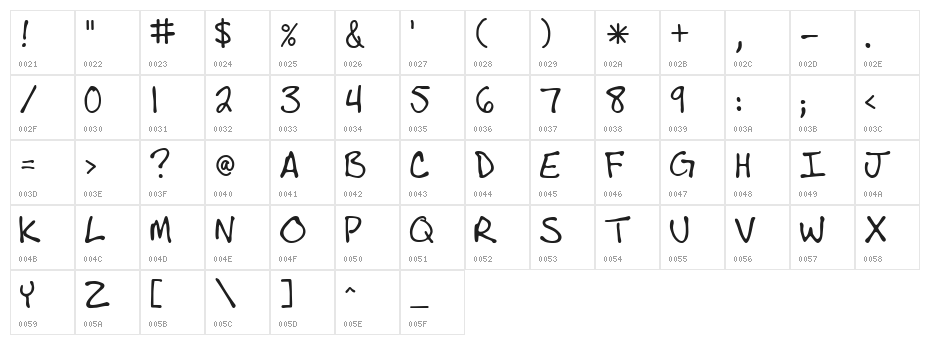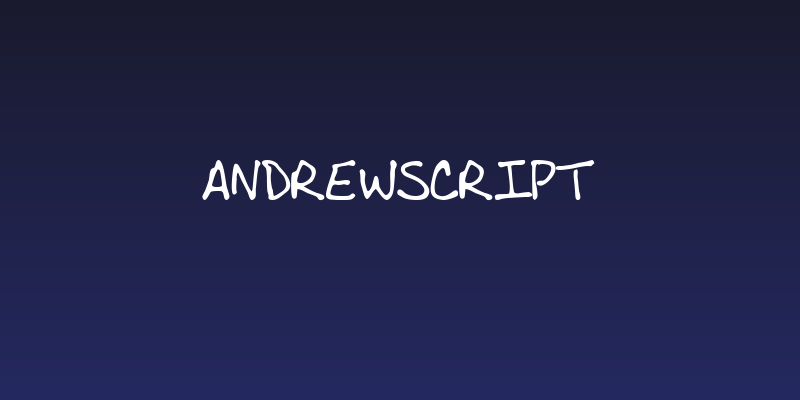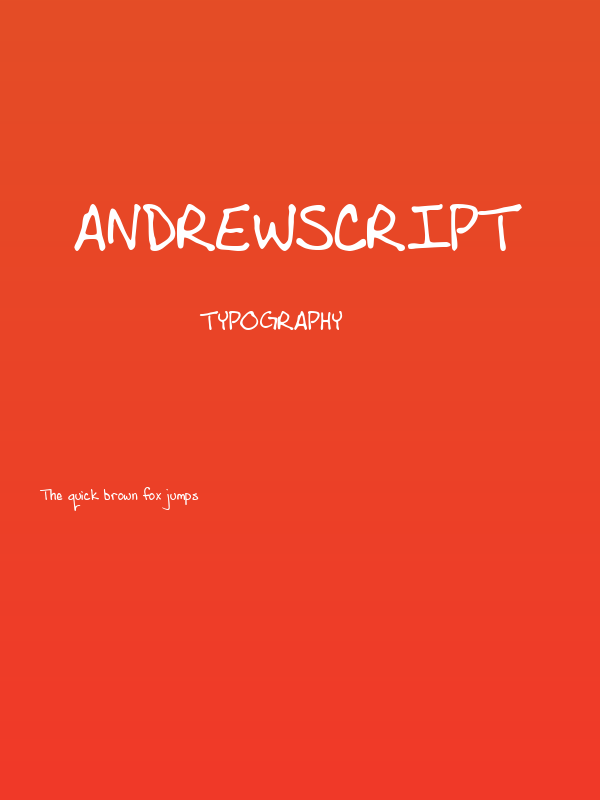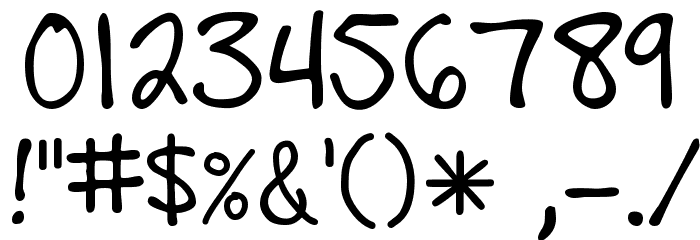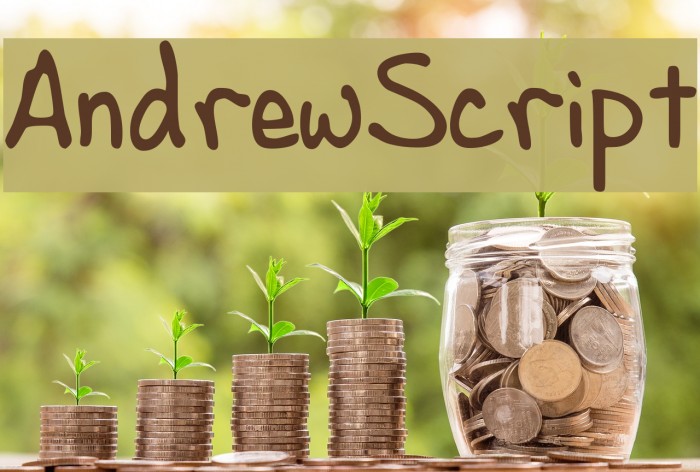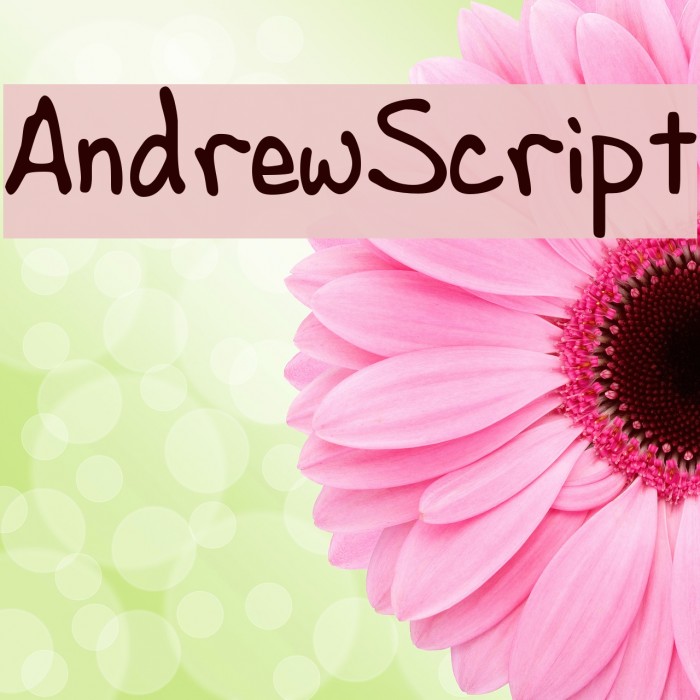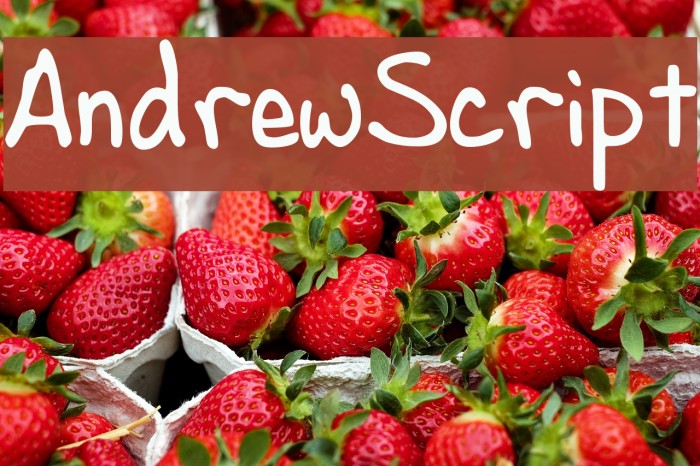
AndrewScript Font
| Gesamtstil | Casual |
| Anwendungsfall | Headlines, Informal text, Personal projects |
| Vorgeschlagene Projekte | Ideal for invitations, greeting cards, personal branding, and informal communications. |